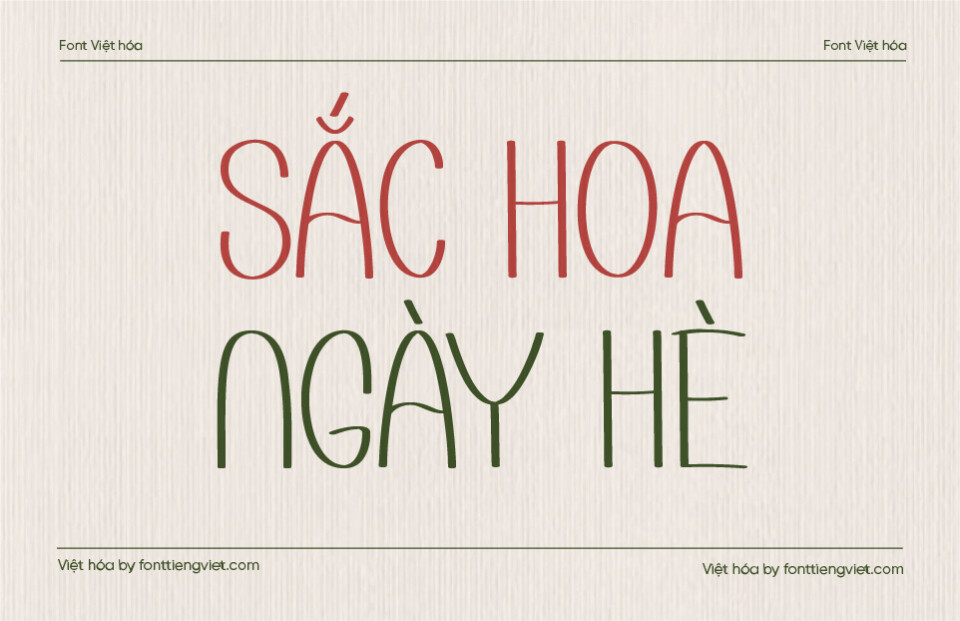
Font Việt hóa 1FTV VIP First Summer – Bộ Font Chữ Tuyệt Đẹp Cho Mùa Hè Năng Động Chào mừng các bạn đến với thế giới sáng tạo của những con chữ đầy màu sắc. Trong bài viết hôm nay, chúng tôi xin giới thiệu một siêu phẩm không thể bỏ qua đối với các nhà thiết kế và người yêu đồ họa: Font Việt hóa 1FTV VIP First Summer. Đây là bộ Font Miễn Phí mang phong cách hiện đại, trẻ trung, rất phù hợp để làm mới các dự án thiết kế trong dịp hè này. Với đường nét thanh thoát nhưng không kém phần phá cách, bộ font này hứa hẹn sẽ mang đến luồng gió mới cho các tác phẩm của bạn, từ những tấm thiệp mời cho đến các banner quảng cáo sự kiện sôi động.Khám phá sức hút của Font Việt hóa 1FTV VIP First SummerMùa hè luôn là khoảng thời gian của sự nhiệt huyết và những chuyến đi đầy trải nghiệm. Font Việt hóa 1FTV VIP First Summer được tạo ra để phản ánh chính xác tinh thần đó. Điểm đặc biệt của bộ font này nằm ở khả năng tương thích cao với tiếng Việt, giúp người dùng không còn lo lắng về lỗi hiển thị dấu hay các ký tự đặc biệt vốn thường gặp ở các font nước ngoài. Từng nét chữ được chăm chút tỉ mỉ để giữ được sự mềm mại tự nhiên, giúp nội dung truyền tải trở nên gần gũi và dễ chạm đến cảm xúc của người xem hơn bao giờ hết.Ứng dụng đa dạng trong học tập và thiết kế đồ họaĐối với các bạn học sinh và sinh viên, Font Việt hóa 1FTV VIP First Summer là một công cụ đắc lực để trang trí bài thuyết trình hoặc làm báo tường kỹ thuật số. Font chữ này giúp các tiêu đề bài học trở nên nổi bật và thu hút sự chú ý của thầy cô lẫn bạn bè. Trong lĩnh vực chuyên nghiệp, các designer thường sử dụng bộ font này cho các ấn phẩm truyền thông mạng xã hội như Facebook, Instagram hay thiết kế bao bì sản phẩm mang tính biểu tượng mùa hè. Sự linh hoạt giữa các nét đậm và nhạt tạo nên sự cân bằng hoàn hảo cho mọi bố cục trình bày.Tại sao bạn nên chọn Font Việt hóa 1FTV VIP First Summer?Việc lựa chọn một font chữ phù hợp chiếm đến 50% sự thành công của một bản thiết kế. Font Việt hóa 1FTV VIP First Summer không chỉ đẹp về mặt thẩm mỹ mà còn rất dễ sử dụng trên nhiều phần mềm khác nhau như Photoshop, Illustrator hay Canva. Khả năng hiển thị sắc nét trên cả màn hình điện thoại và máy tính giúp thông điệp của bạn luôn rõ ràng. Ngoài ra, tính năng Việt hóa chuẩn xác giúp bạn tiết kiệm thời gian chỉnh sửa dấu câu, tập trung hoàn toàn vào việc sáng tạo ý tưởng mới lạ và độc đáo cho dự án của mình.Lưu ý khi sử dụng font chữ trong các dự án thực tếDù Font Việt hóa 1FTV VIP First Summer rất đẹp nhưng bạn nên lưu ý kết hợp với các font chữ không chân (sans-serif) đơn giản cho phần nội dung dài để đảm bảo tính dễ đọc. Hãy thử nghiệm việc thay đổi màu sắc rực rỡ như vàng nắng, xanh biển hoặc cam san hô để làm bật lên chất “summer” đặc trưng. Việc sử dụng font một cách thông minh sẽ giúp bạn tạo ra những sản phẩm chuyên nghiệp, ghi dấu ấn cá nhân mạnh mẽ trong mắt người xem và đối tác tiềm năng trong tương lai gần.Kết luận về bộ Font Việt hóa 1FTV VIP First SummerTóm lại, bộ Font Việt hóa 1FTV VIP First Summer là lựa chọn hàng đầu cho bất kỳ ai đang tìm kiếm sự phá cách và tươi mới. Hy vọng rằng với chia sẻ này, bạn sẽ có thêm một tài nguyên quý giá trong kho tàng thiết kế của mình. Đừng quên truy cập thường xuyên để cập nhật thêm nhiều bộ Font Miễn Phí, Font Việt Hóa, Font Việt hóa 1FTV VIP First Summer chất lượng khác. Chúc bạn có những trải nghiệm thiết kế tuyệt vời và đầy cảm hứng sáng tạo với bộ font đặc biệt này. Hãy bắt đầu dự án mùa hè của bạn ngay hôm nay để thấy được sự khác biệt vượt trội mà nó mang lại cho tác phẩm nghệ thuật của mình nhé!
Font Việt hóa 1FTV VIP First Summer